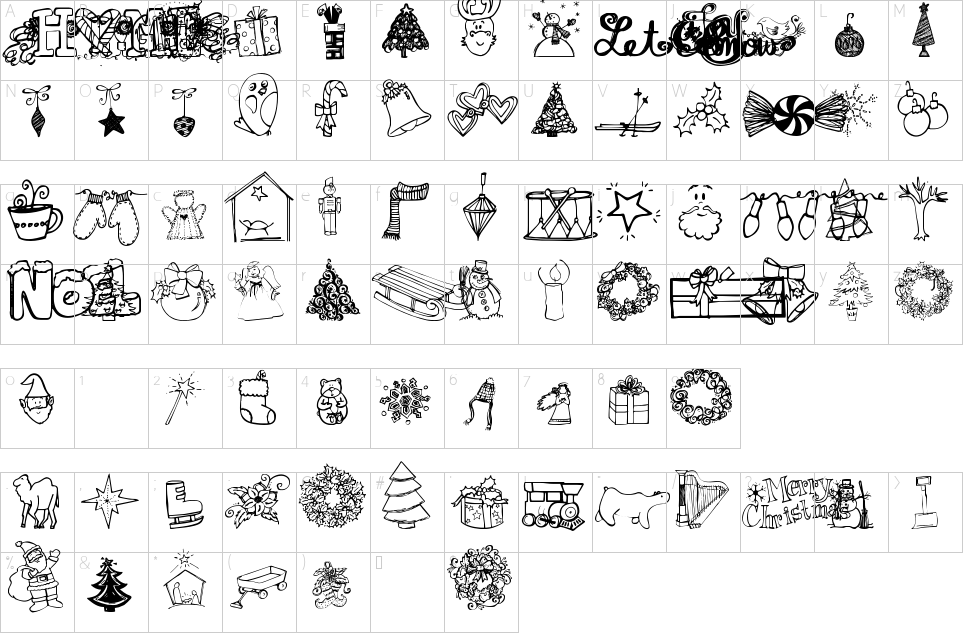
A fonte Janda Christmas Doodles é uma deliciosa adição para quem está buscando uma fonte gráfica para festas de Natal e ocasiões especiais. Desenhada pela incrível Kimberly Geswein, esta fonte aderece ao seu design delicado e cheio de graça, com traços de traçado artesanal que dão um toque único e personalizado aos seus trabalhos. Janda Christmas Doodles é uma fonte ideal para textos ornamentais, cartões de Natal, ilustrações em papel, e qualquer outra ocasião especial. Com mais de 53 mil downloads, não há dúvida de que esta font é uma opção segura e popular. Fique à vontade para descobrir o brilho inconfundível da Janda Christmas Doodles para enfeitar e adicionar um toque especial a seus projetos.